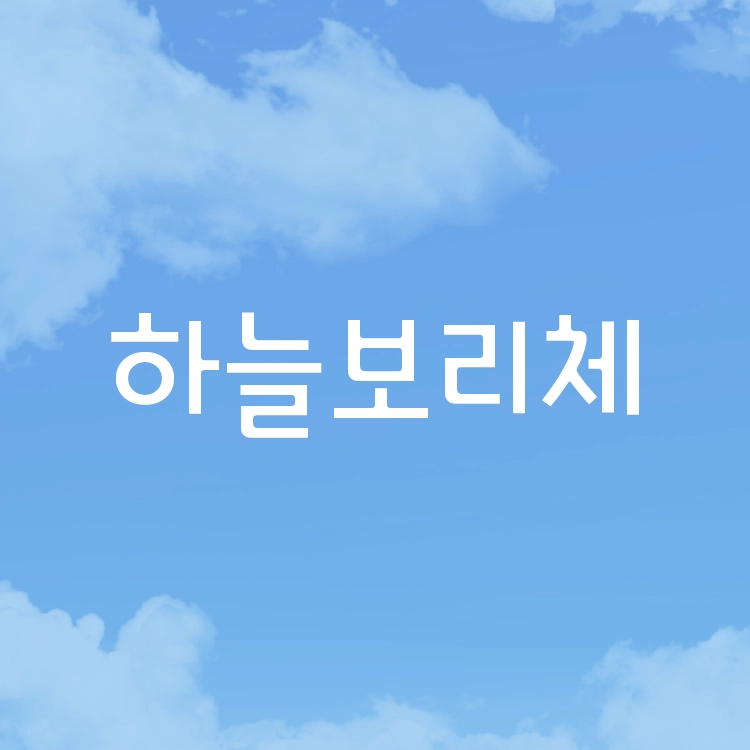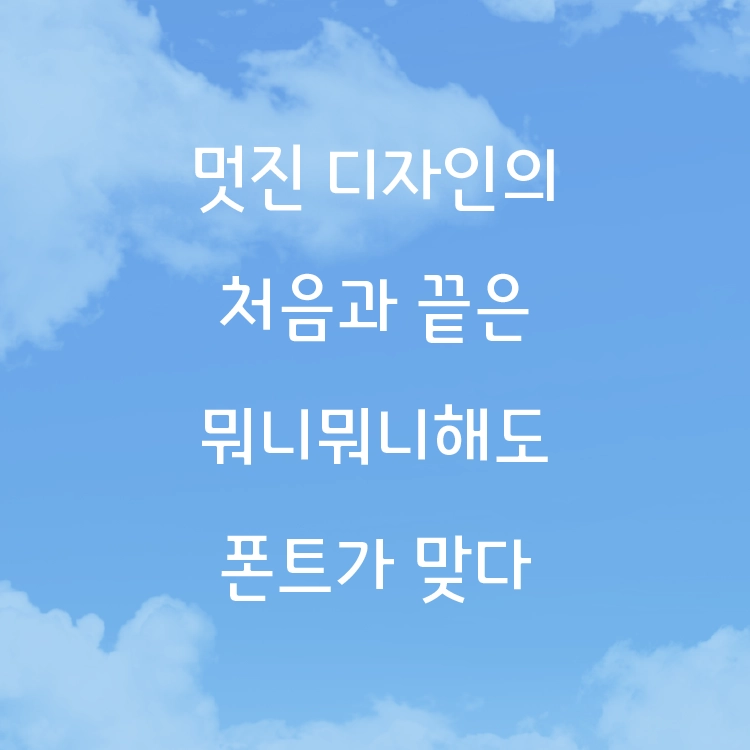
하늘보리체
보리차 No.1, 웅진식품 차류 브랜드 1위의 하늘보리 B.I 특징을 담은 '하늘보리체'
하늘보리체는 자연 그대로를 담아 만들어진 하늘보리의 이미지를 리듬감이 느껴지는 탈네모틀 구조로 표현해 자소의 흐름이 자연스러운 웅진식품 차류 브랜드 아이덴티티를 반영한 디자인입니다.